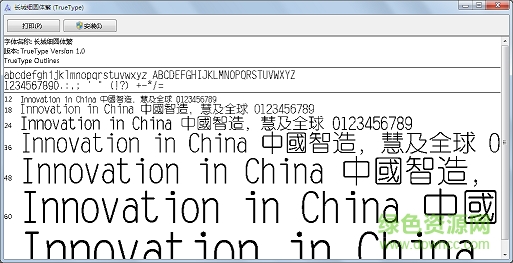
tyenround light字體就是長(zhǎng)城細(xì)圓體繁體字體,字體清晰,粗細(xì)一致,筆畫轉(zhuǎn)角柔和,看上去樸實(shí)自然,雅俗共賞,需要的小伙伴趕緊下載吧!
圓體是國(guó)內(nèi)的一種說法,實(shí)際上在英文書法中并沒有圓體這一說,所謂圓體是英文書法的延伸及日?;^為隨意。國(guó)內(nèi)所謂的圓體字形似Copperplate,但沒有粗細(xì)變化和華麗的修飾,是不能比的。圓體是一種日常使用的手寫體。